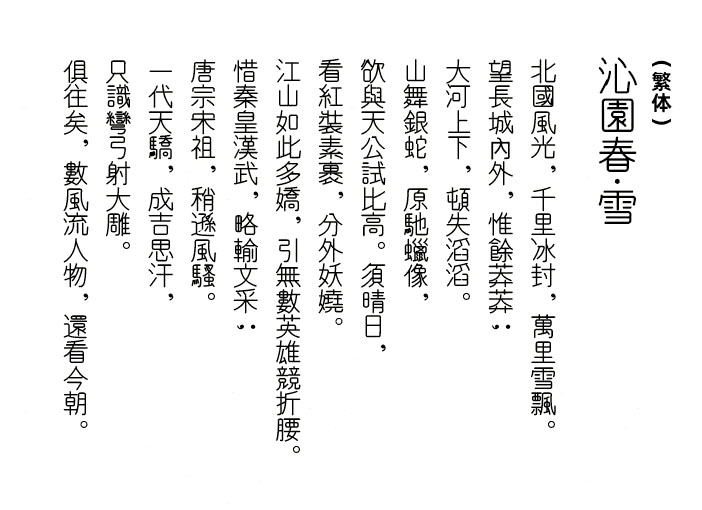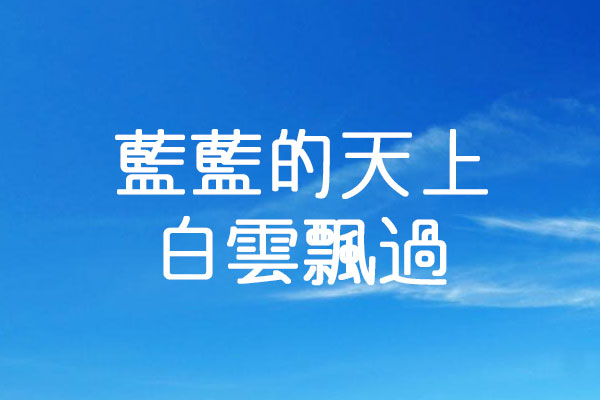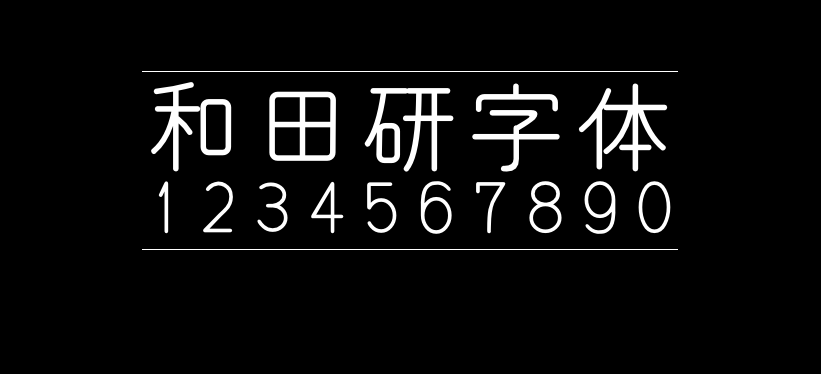
和田研字体
和田研字体(和田研細丸ゴシック / 和田研中丸ゴシック;WadaLabChuMaruGo2004Emoji)是WadaLab,RareEarth(日本)发布于2004年的一款字体,年代相对久远,但是迄今为止依然在持续维护更新中,最新的版本发布于2020年02月24日。以简单的元素来表达字体的美感且每一个字体的直角转折处都以椭圆角来做替代,整个字体的设计都充满了浓浓的古典风格。
在字体包里面包含了两款字体,分别是“和田研细丸”和“和田研中丸”,细丸笔画较细,而中丸笔画较粗。而字体文件上带有P的,则是代表等宽字体。这款字体虽然是日本的,但是包含的繁体字符还是比较全的,常用字基本都覆盖了。